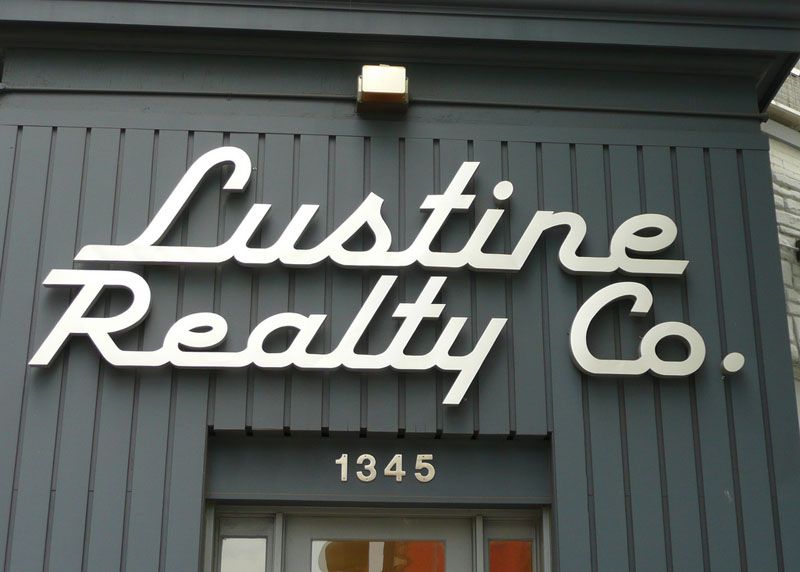
Почему шрифт — важный элемент в рекламе, и при чем тут арбитраж
Шрифт — влиятельная вещь, которая воздействует на восприятие текста, а значит имеет немаловажное значение в рекламе товаров и услуг. Если нам не нравится внешний вид текста, мы можем вовсе его проигнорировать. Какие шрифты привлекают внимание, и есть ли свой шрифт арбитража — читайте в нашем материале.
Уникальность через текстШрифт — это элемент айдентики, одна из ключевых частей фирменного стиля компании. Существуют бесплатные и платные шрифты, а еще кастомные, которые компании разрабатывают сами для себя. Ниже мы будем рассматривать ценность именно кастомного шрифта, поскольку его разработка требует немалых ресурсов, и люди задаются вопросом «Ради чего? Это же просто шрифт». Но это далеко не так.
Какие функции выполняет кастомный шрифт? Прежде всего он создает бренду уникальный образ и выделяет его среди конкурентов. Он отображает характер компании на разных площадках, как онлайн, так и офлайн.
Хорошо проработанный шрифт помогает выработать единый стиль у компании, ту самую айдентику. И немаловажно, что он помогает бороться с недобросовестными конкурентами, которые не гнушаются использовать чужую марку и подгонять оформление своего товара под стиль другого уже востребованного бренда (вспомните, как часто мы видим вывески «Шаурма», стилизованные под McDonald’s). Но полностью скопировать кастомный шрифт трудно, и отличия все равно можно заметить.
Компании необязательно полностью разрабатывать шрифт для всего алфавита, можно ограничиться несколькими буквами только для лого. Но крупные бренды с большими бюджетами не жмутся и могут позволить себе создать целые шрифтовые системы: например, Apple сделали для себя шрифт San Francisco, Microsoft — Segoe, а Google сразу два — Product Sans и Roboto.
Кастомные шрифты могут применяться и как графический элемент в лого. Так поступила компания Sun Microsystems, занимающаяся разработкой программного и аппаратного обеспечения.
В фирменном изображении использована амбиграмма со словом Sun, при этом в самом знаке есть только буквы u и n, из которых визуально вытекает и s.
Подходящий шрифт помогает компании объединить в одну систему разные каналы информации (реклама в соцсетях, на сайте, других площадках), усилить и подчеркнуть идентичность бренда, выделив его на фоне остальных. Но стиль текста помогает и в делах более мелкого масштаба, например, в продвижении приложений в сторах.
Тут важно отметить, что разработка собственного шрифта — занятие очень хлопотное, а главное дорогостоящее. Поэтому чаще всего компании используют уже созданные варианты.
Особенности восприятия шрифтов«Шрифт — эмоциональный инфлюенсер в нашем мире. Бренд — это типографика», — считает старший креативный директор по шрифтам в Monotype Фил Гарнем.
Как доказали нейробиологи, за распознавание значения слов отвечает височная доля мозга, которая также ответственна и за обработку эмоций.
Поэтому визуальный вид текста напрямую может влиять на настроение человека.
«Позитивный эмоциональный отклик рождается при взгляде на более мягкие и узнаваемые типы шрифтов. А шрифты с заостренным начертанием вызывают негативные эмоции», — уверен основатель и гендиректор Neurons Томас Ремсой (компания по исследованиям в нейробиологии, в том числе изучала влияние шрифтов на человека).
По мнению Ремса, некоторые шрифты уже давно соотносятся с определенной сферой. Например, Cotford ассоциируется с индустрией моды и роскоши, Gilroy — с IT-сферой, а FS Jack — с банковскими и финансовыми учреждениями.
С учетом психологического воздействия шрифты (и их характеристики) можно поделить на 4 группы. Каждую из них мы обозначили в соответствии с образами, которые возникают при виде текстов, написанных этими шрифтами.
Сила, энергия и деловой тонТакие ощущения обычно возникают от прямого вытянутого шрифта. Но он мало подходит для рекламы немассовой и оригинальной продукции, поскольку будет выглядеть скучно, невзрачно и безлико.
Если вы все же выбрали такой шрифт, то его недостатки придется компенсировать цветовыми решениями, чтобы разнообразить текст визуально.
Подобные чувства возникают при взгляде на строгие квадратные шрифты, которые часто используются в рекламе промышленных товаров и технологий. Никакой легкости или простоты, ведь техника — это не игрушка, а значит, разговор с покупателем должен быть серьезным. Текст, написанный в таком стиле, будет нарочно подчеркивать важность и значимость информации.
Доброта, уют и довериеЭти образы часто ассоциируются с округлым шрифтом. В противовес к суровому вытянутому и строгому квадратному тексту этот стиль передает доброжелательное отношение компании к своим клиентам. Так что о заботе и взаимопонимании лучше писать только округлым текстом.
Счастье, красота и уникальностьТакие образы транслируют два вида шрифтов. Один из них — наклонный с виньетками, который любят, например, в бьюти-индустрии.
Благодаря курсиву информация воспринимается не в серьезном тоне, а виньетки словно «заигрывают« с покупателем, что в сумме вызывает приятные ассоциации.
Да пребудет с вами шрифт
В конечном счете, выбор шрифта остается за вами, но имейте в виду: ваш фирменный и маркетинговый шрифт должен быть мощным, разборчивым и приятным. Более того, то, что написано этим шрифтом, должно быть ценным, интересным и важным для ваших потенциальных клиентов и клиентов.
Шрифты с засечками считаются более строгими, даже в Google Docs по умолчанию Calibri, и только в официальных документах по-прежнему используют Times New Roman.